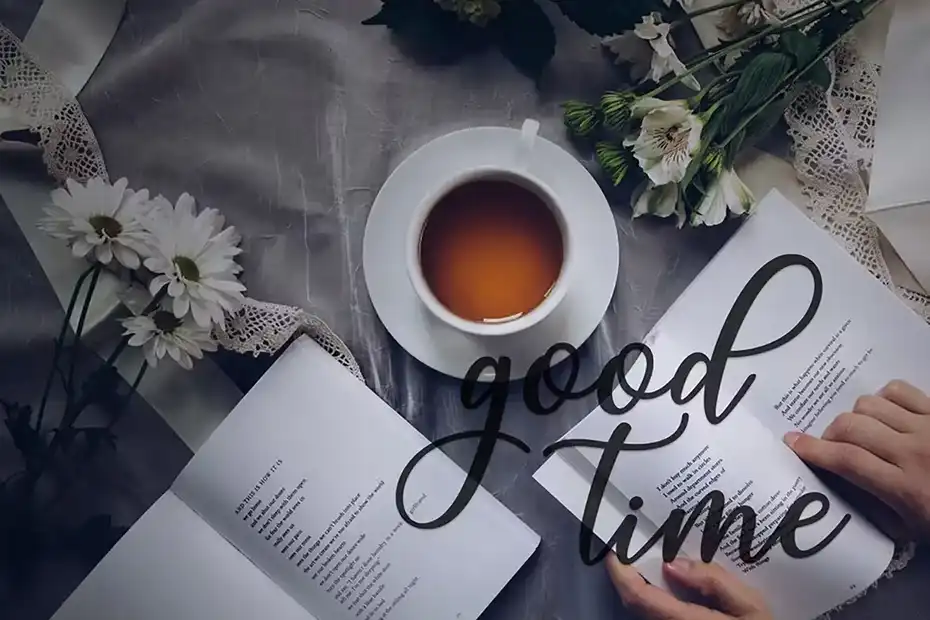
دانلود فونت انگلیسی جادویی magic script font
فونت انگلیسی جادویی magic script font : این مجموعه شامل یک فونت انگلیسی دست نویس است که برای لوگو، برندینگ، کارت دعوت عروسی، مجله، ماگ، کارت ویزیت، نقل قول، پوستر و غیره مناسب میباشد.